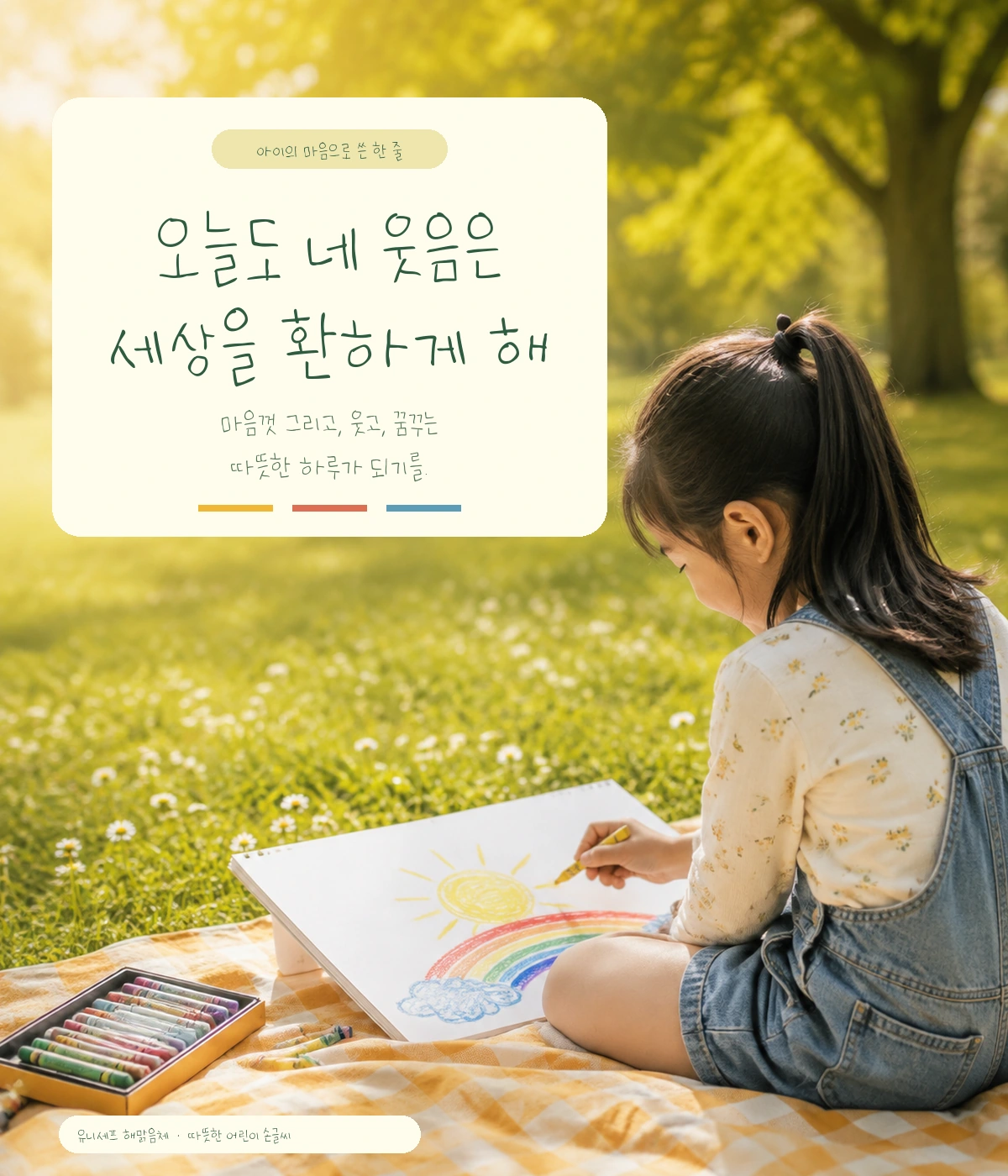
유니세프 해맑음체 — 사단법인 유니세프 한국위원회에서 배포하는 무료 폰트입니다. 손글씨 대회 유아부 최우수상을 받은 어린이의 필체를 그대로 옮긴, 밝고 따뜻한 손글씨체
유니세프 한국위원회가 2025년 세계 어린이의 날에 공개한 서체입니다. 만들어진 과정이 특별합니다. 제1회 유니세프 어린이 손글씨 쓰기 대회에서 아이들이 유엔아동권리협약을 읽으며 글씨를 썼고, 그 가운데 유아부 최우수상을 받은 우승헌 어린이의 필체가 이 서체가 됐습니다. 수상한 아이들이 산돌 사옥을 찾아와 원도 작업에 직접 참여하기도 했습니다.
산돌은 밝고 활달한 연필 필체를 살리는 데 초점을 맞췄습니다. 글자 크기와 형태의 편차를 정교하게 분석해 손으로 쓴 자연스러움을 남겼고, 아이가 그린 낙서와 기호를 딩벳으로 함께 넣었습니다. 파일에서 재어 보면 가로획이 세로획보다 굵고 받침 유무에 따라 글자 높이가 크게 달라지는 탈네모틀이라, 글줄이 공책에 쓴 것처럼 오르내립니다.
같은 대회에서 나온 형제 서체가 둘 더 있습니다. 대상을 받은 김소율 어린이의 도담체와 초등부 최우수상 김서우 어린이의 꾸러기체입니다. 현대 한글 11,172자를 모두 담았고 무료로 배포됩니다.